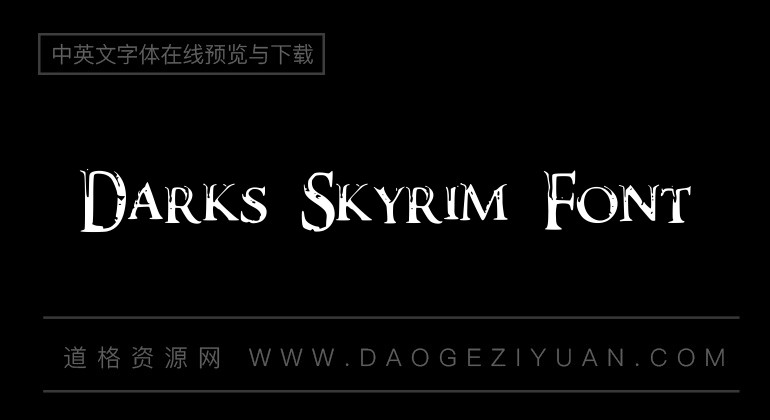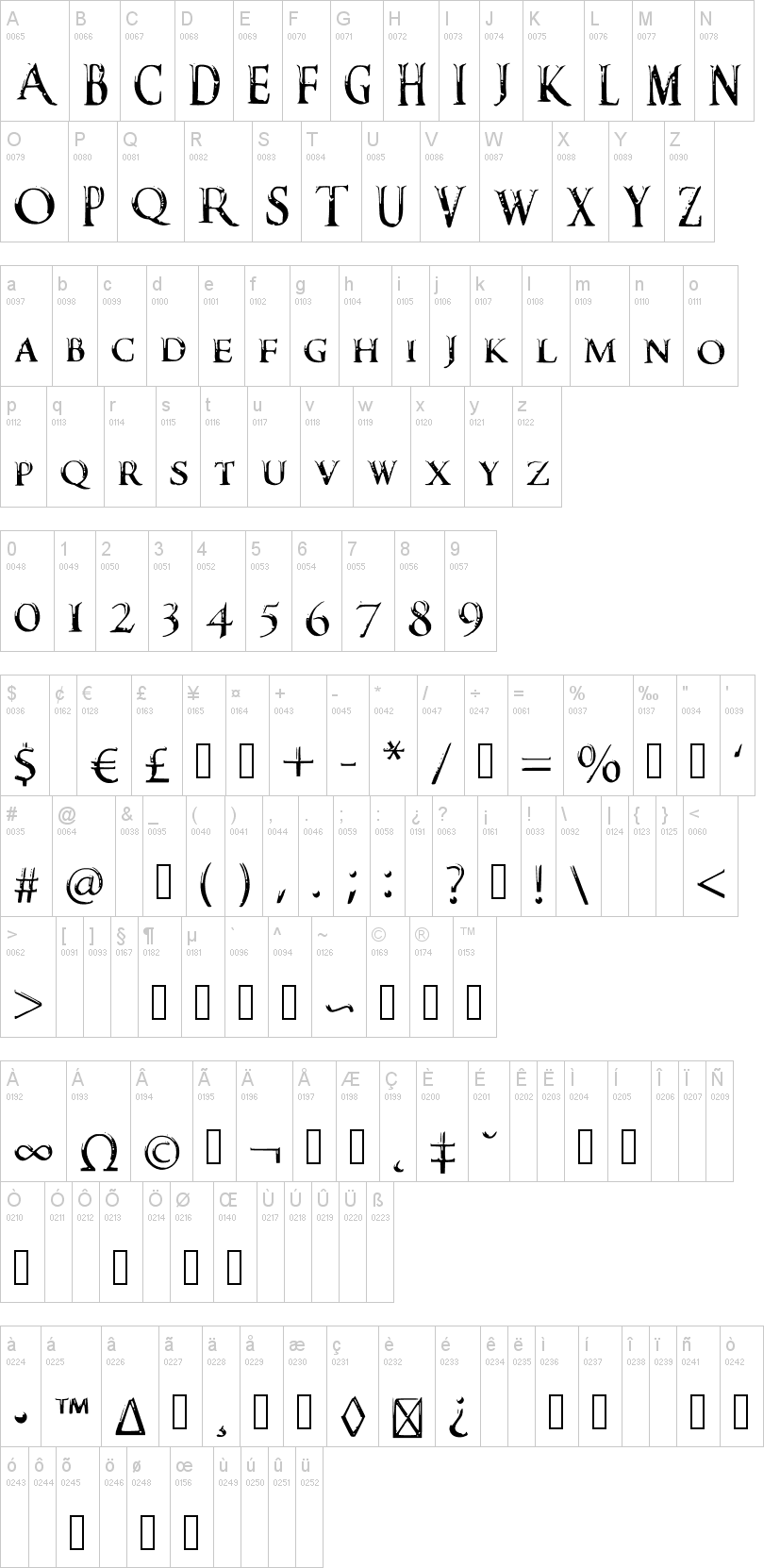
Darks Skyrim Font是一款针对游戏《上古卷轴5:天际》(The Elder Scrolls V: Skyrim)设计的字体。这款字体的设计灵感来自于游戏中的文本和标志,并结合了一些艺术家的创意。该字体是一种苍白和神秘的字体,呈现出一种中世纪风格的感觉,适合用于游戏、电影、书籍、海报和其他与奇幻、神秘或中世纪相关的设计项目中。Darks Skyrim Font包含大小写字母、数字、标点符号和其他常用字符,可免费下载和使用。内容介绍
Darks Skyrim Font是一款非常不错的手写艺术字体,具有很好的视觉感,适合于文化类的宣传设计、商业类品牌的广告和产品包装设计以及个性化文字排版等较多场景。